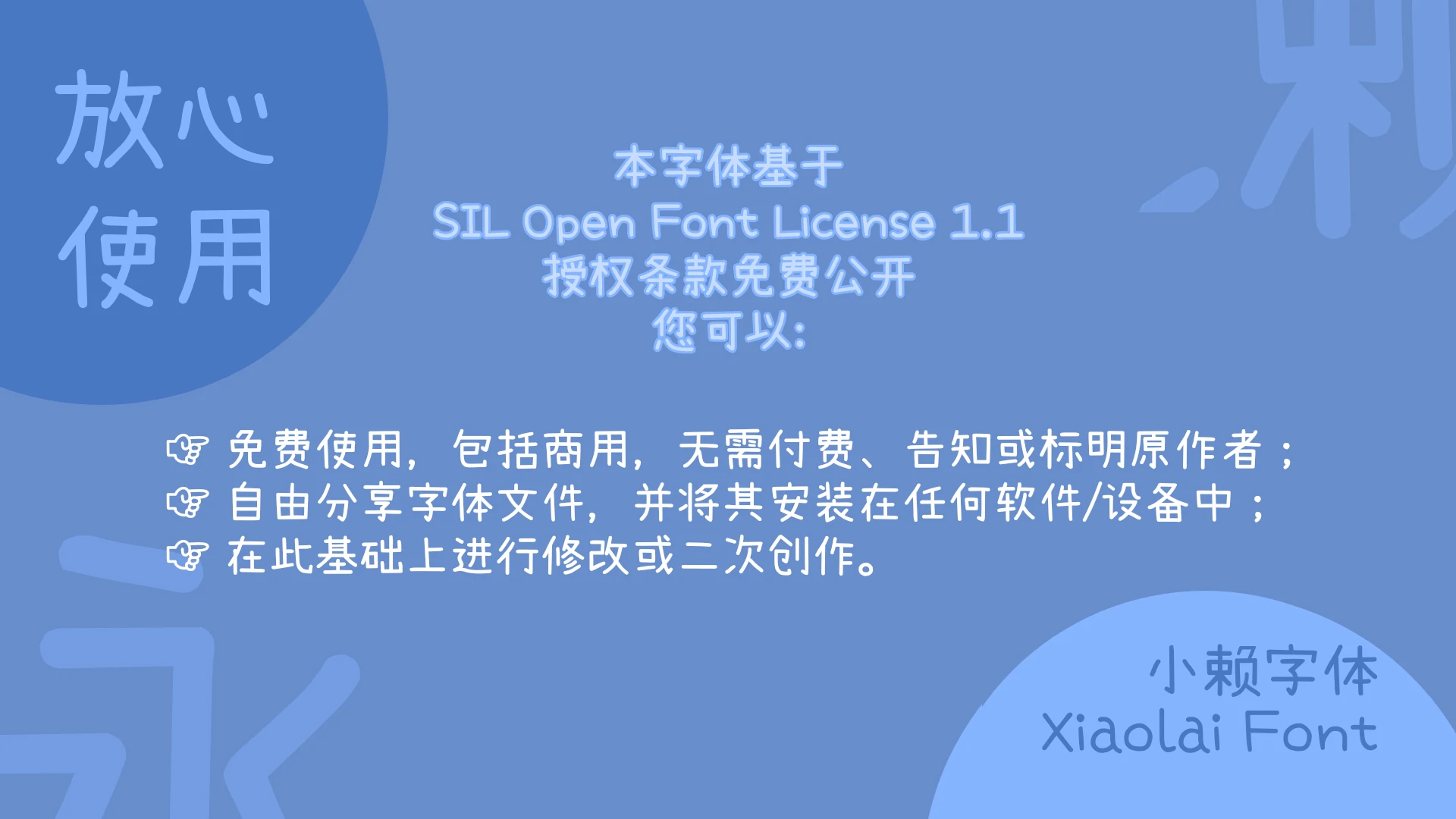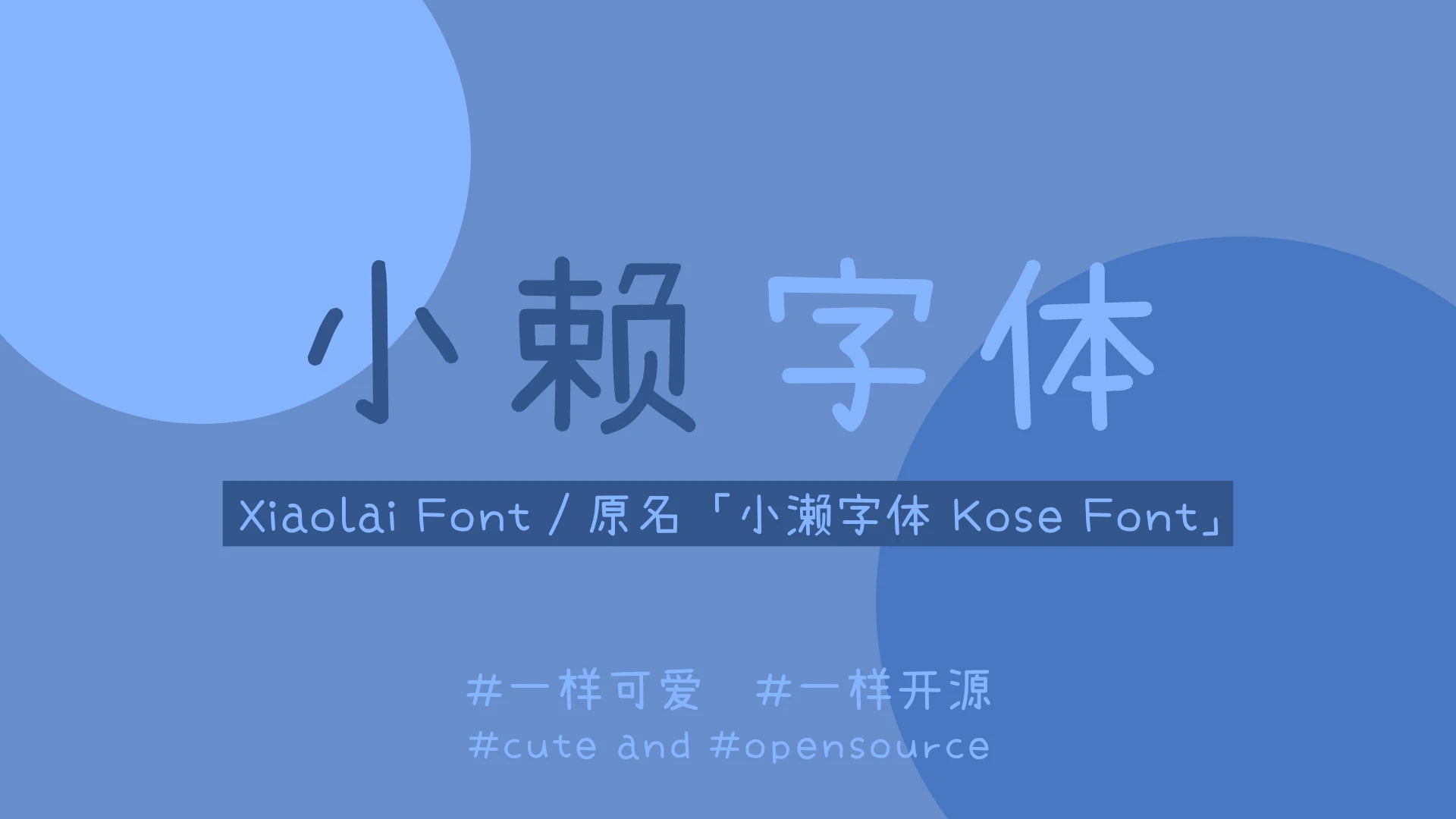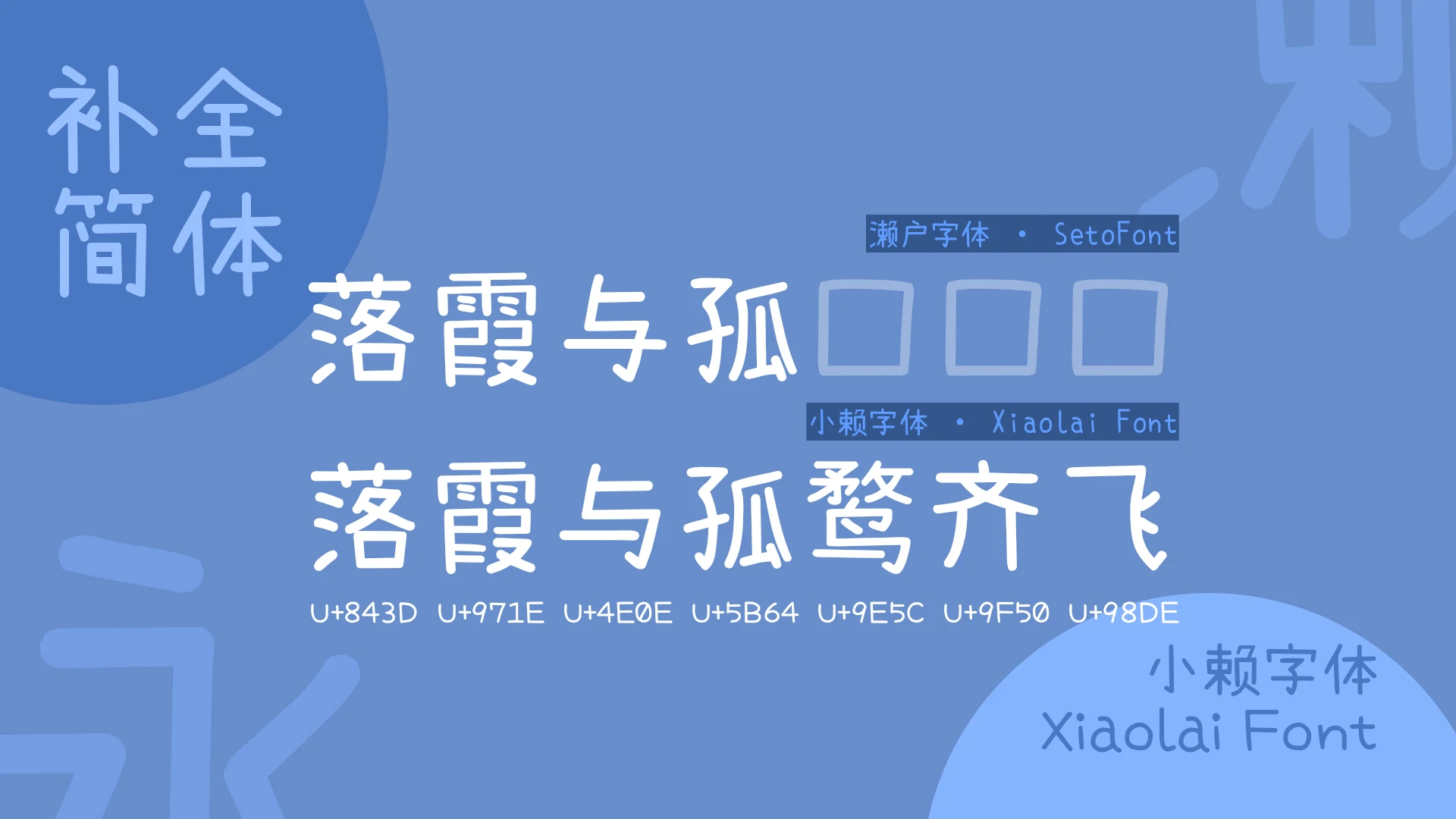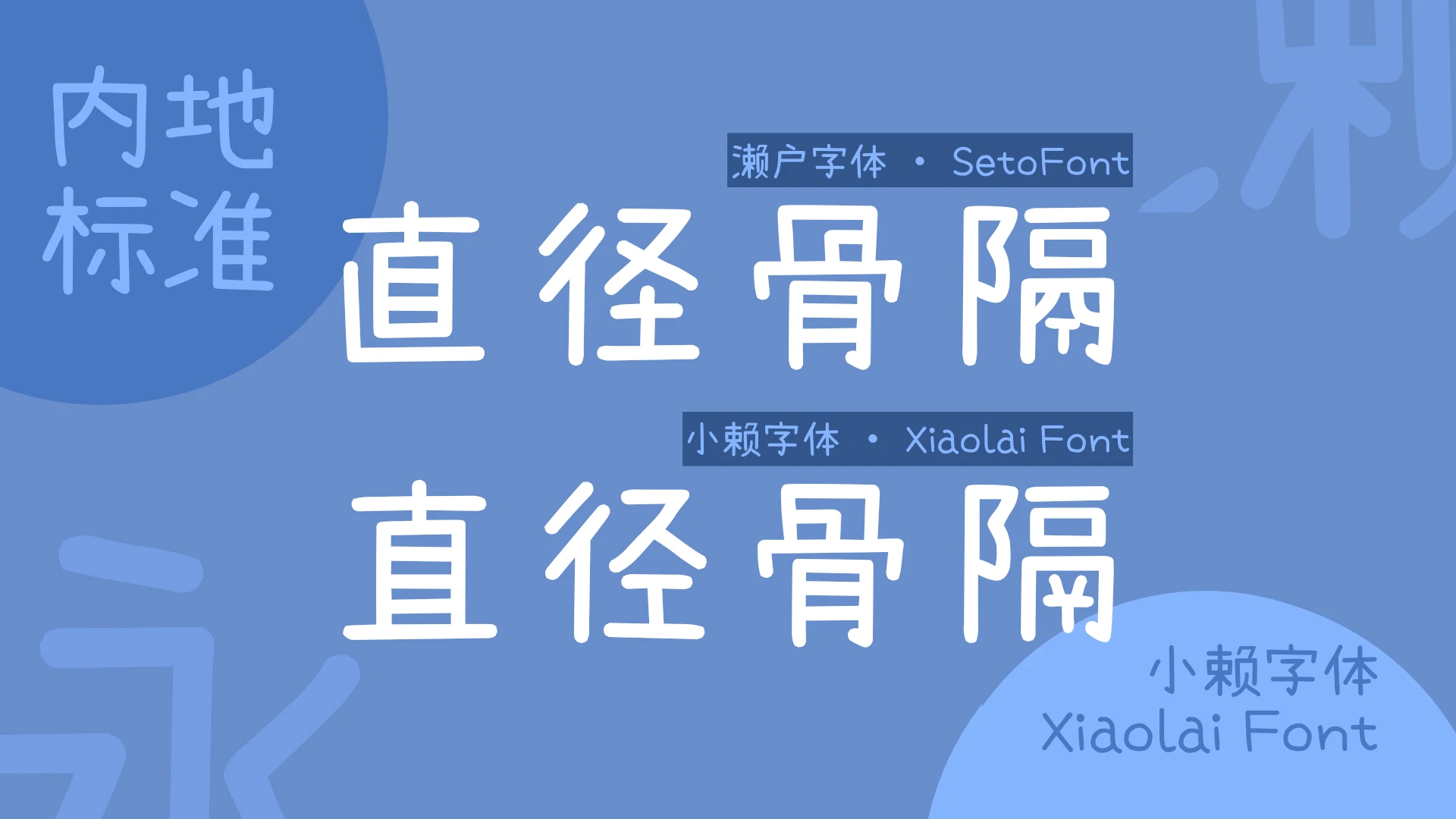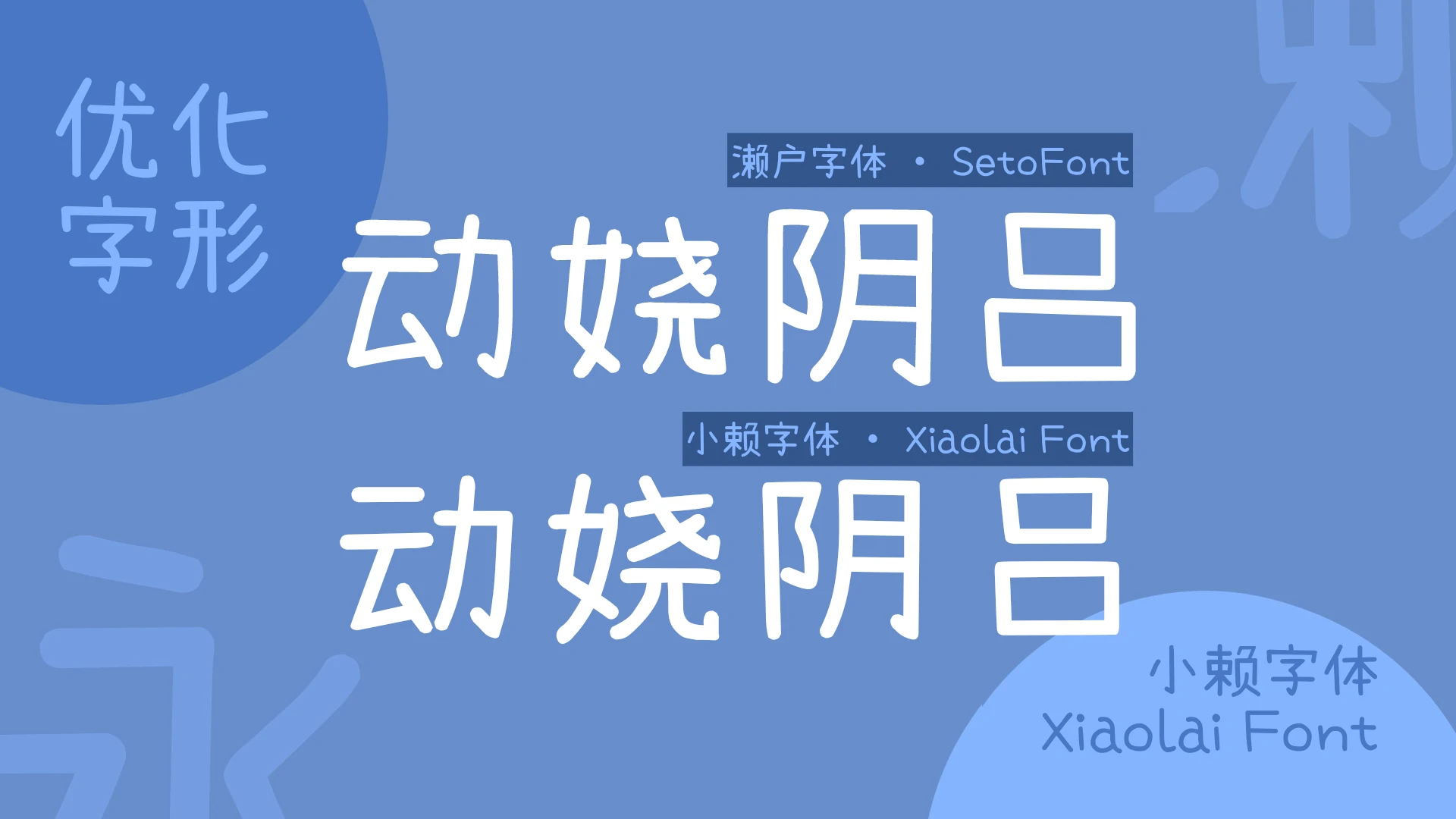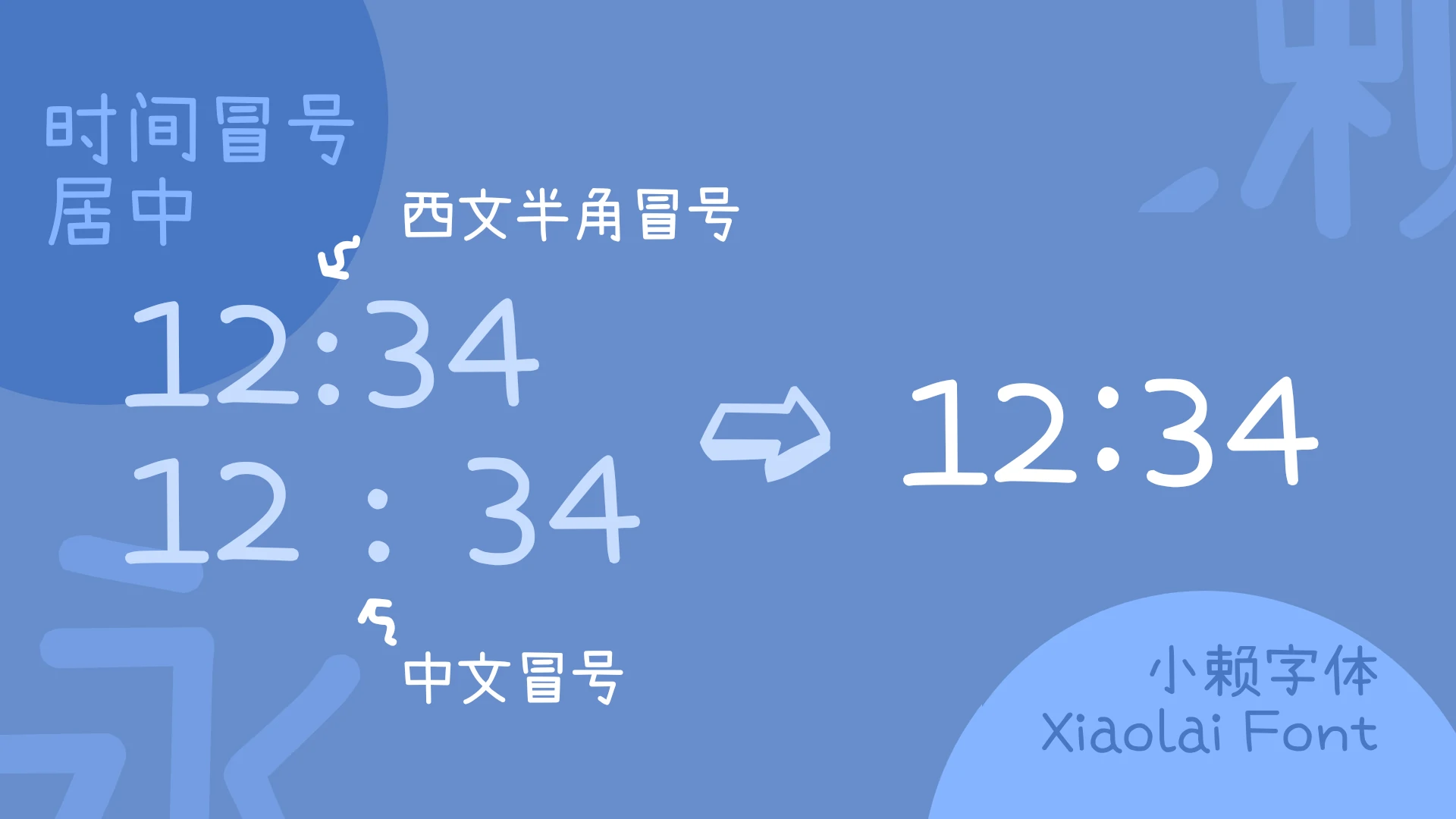
小赖字体 Mono
别称:Xiaolai Font Mono
概述
小赖字体 / 小賴字體 / シャオライ / Xiaolai Font
濑户字体 是由日本的业余字体设计师 瀬戸のぞみ 制作,支持 JIS 第一至第四级,支持繁体和简体中文(部分)。目前最新的版本是 2014 年 9 月 24 日的 6.20 版本,原作者已经很久不更新了。
后来, Max 在原来的「濑户字体」基础上,推出了 内海字体 ,补齐了台湾教育部门列出的 4808 个常用字,并增加了闽南语、粤语常用字,弥补了繁体中文地区常用字缺字缺憾。
但是,这款可爱的开源字体,仍然缺少一部分简体字,这对于大陆的用户来说,可能会造成一些不便。
于是,本人开启了 “濑户内海字体简体补全计划” ,旨在补足 濑户字体 缺少的简体字。 小赖字体 是这一计划的延续。
本字体项目原名为 「小濑字体」 ,后来由于很多人都把「濑」打成「赖」,索性把「氵」去掉,改名 「小赖字体」 。
字体概况
本字体是 濑户字体 的简体中文化改良,利用濑户字体里原有的部件,对原字体中缺少的汉字进行补足,主要为 GB2312 及《通用规范汉字表》里的汉字,其余的汉字、谚文、特殊符号用 cjkFonts 全濑体 补全。现有 CJK 基本区汉字 20992 个,扩展 A 区汉字 6592 个,另有零星扩展 B~G 区汉字。
该字体可显示 GB 18030-2022 实现级别 2 范围内的全部汉字,以及《通用规范汉字表》里的全部汉字(共 8105 个),满足中国大陆用户的使用需要。此外可显示日文假名、谚文 (韩文、朝鲜文) 音节和思源黑体可以显示的特殊符号字体。